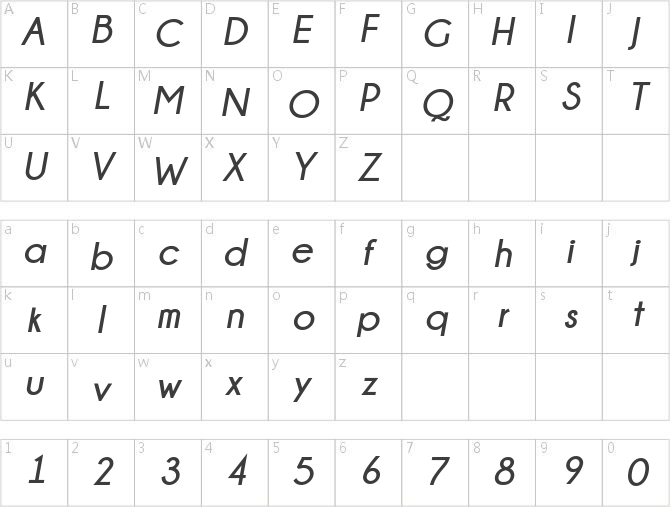
Champagne & Limousines Bold Ital 詳情頁(yè)
Champagne & Limousines Bold Ital字體字庫(kù)是一款讓人賞心悅目、百看不厭的英文字體,適合各類廣告和產(chǎn)品包裝設(shè)計(jì)應(yīng)用,字體大小0.1MB,格式為ttf字體,上傳用戶是晴朗,作者/版權(quán)方為未知